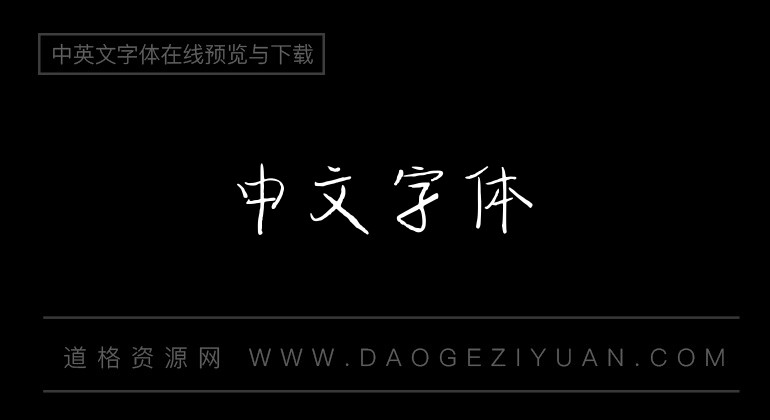
彩虹屁男孩字体是一款漂亮的手写体字体,由著名的设计师Juan Casco创作。它具有简洁、可爱、活泼的特点,可以用于各种类型的文档和设计项目。字体的设计风格为简约、柔和,让人联想到温暖、温馨的家庭氛围。它也具有良好的可读性和可访问性,可以用于各种文本和图像设计项目中。文件名:CaiHongPiNanHai-2.ttf
彩虹屁男孩是一款非常不错的手写艺术字体,具有很好的视觉感,适合于文化类的宣传设计、商业类品牌的广告和产品包装设计以及个性化文字排版等较多场景。